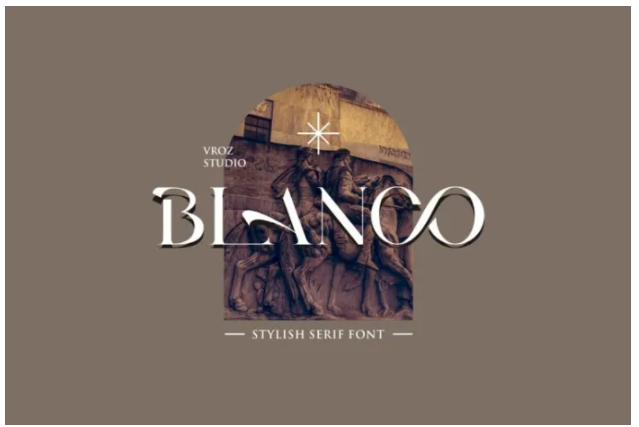
BLANCO - современный стильный шрифт с засечками
BLANCO идеально подойдет для многих проектов: мода, журналы, логотип, брендинг, фотография, приглашения, свадебные приглашения, цитаты, заголовок блога, плакат, реклама, открытка, книга, веб-сайты и т.д.
если вы хотите ввести стильные буквы, вы можете ИСПОЛЬЗОВАТЬ blancoliga.ttf